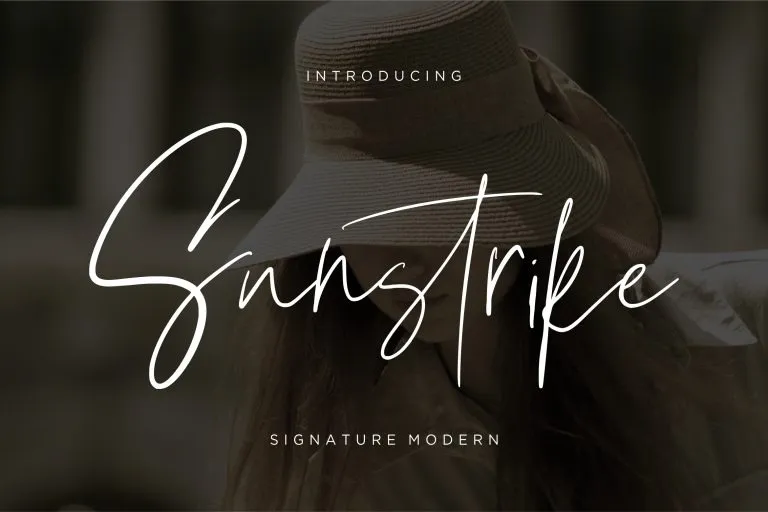
A Sunstrike Font é uma escolha perfeita para quem procura uma fonte script que não apenas expressa originalidade, mas também traz leveza e vivacidade às suas criações. Desenvolvida por 99designs, essa fonte foi criada com impressionantes traços de mão, onde cada curva é cuidadosamente considerada pela sua elegância e alegria visual. Essa fonte se destaca não apenas pela sua beleza aparente em cada letra, mas também pelo seu poder de expressar personalidade. Os designers que usam Sunstrike encontram no texto um reflexo da paixão e do trabalho duro com o qual foram criados, transmitindo alegria e frescor em qualquer tipo de material onde seja aplicada. Para quem está procurando uma fonte moderna e divertida para seus projetos digitais ou impressos, Sunstrike é uma ótima escolha. Não hesite em experimentá-la; ela certamente vai transformar seu design.